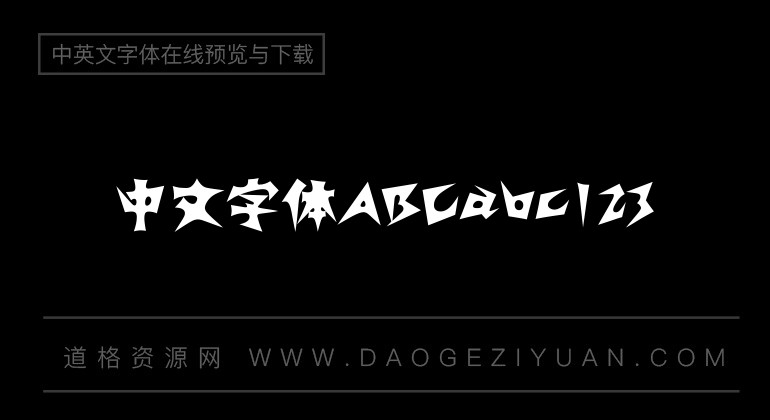
汉仪霹雳体简是一种汉字字体,是汉仪字库公司开发的字体之一。该字体的特点是线条流畅,粗细不同,给人以强烈的视觉冲击力。霹雳体简主要用于标题、标志、广告、海报等大型设计作品中,使文字更具有张力和冲击力。 汉仪霹雳体简的字形设计灵感源于电影海报中常见的大字标题,呈现出一种强烈的视觉冲击感。汉仪霹雳体简有多种字重可供选择,从极细到极粗均可使用,能够适应各种设计需求。 总的来说,汉仪霹雳体简是一款视觉冲击力极强的字体,适合在大型设计作品中使用,可增强文字的视觉效果和传播力。内容介绍
汉仪霹雳体简是一款非常不错的手写艺术字体,具有很好的视觉感,适合于文化类的宣传设计、商业类品牌的广告和产品包装设计以及个性化文字排版等较多场景。